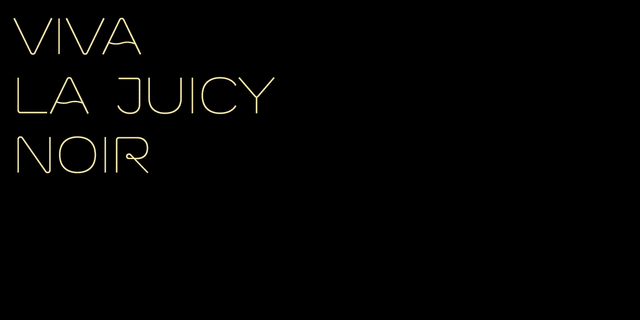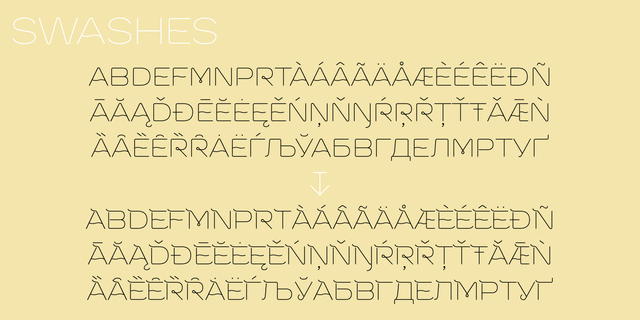
Шрифт Vanyla 4F Unicase содержит 2 начертания и отлично подходит для рекламы, неоновых вывесок, журнальных заголовков и другой акциденции. Разработан Сергеем Ткаченко в 2013 году.
Ассоциации c семейством Vanyla 4F UnicaseКачества и характер:
неоновый, тусовочный, деликатный, плавный, чистый, легкий, прохладный, свежий, модный, городской, тонкий, современный, лаконичный, свободный, невесомый, прозрачный, интимный, клубный, гибкий, гладкий, характерный, оригинальный, необычный, выразительный, молодежный, позитивный, артистичный, музыкальный, популярный, мягкий, изогнутый, нежный, воздушный, проволочный, прелестный, симпатичный, подвижный, динамичный, творческий